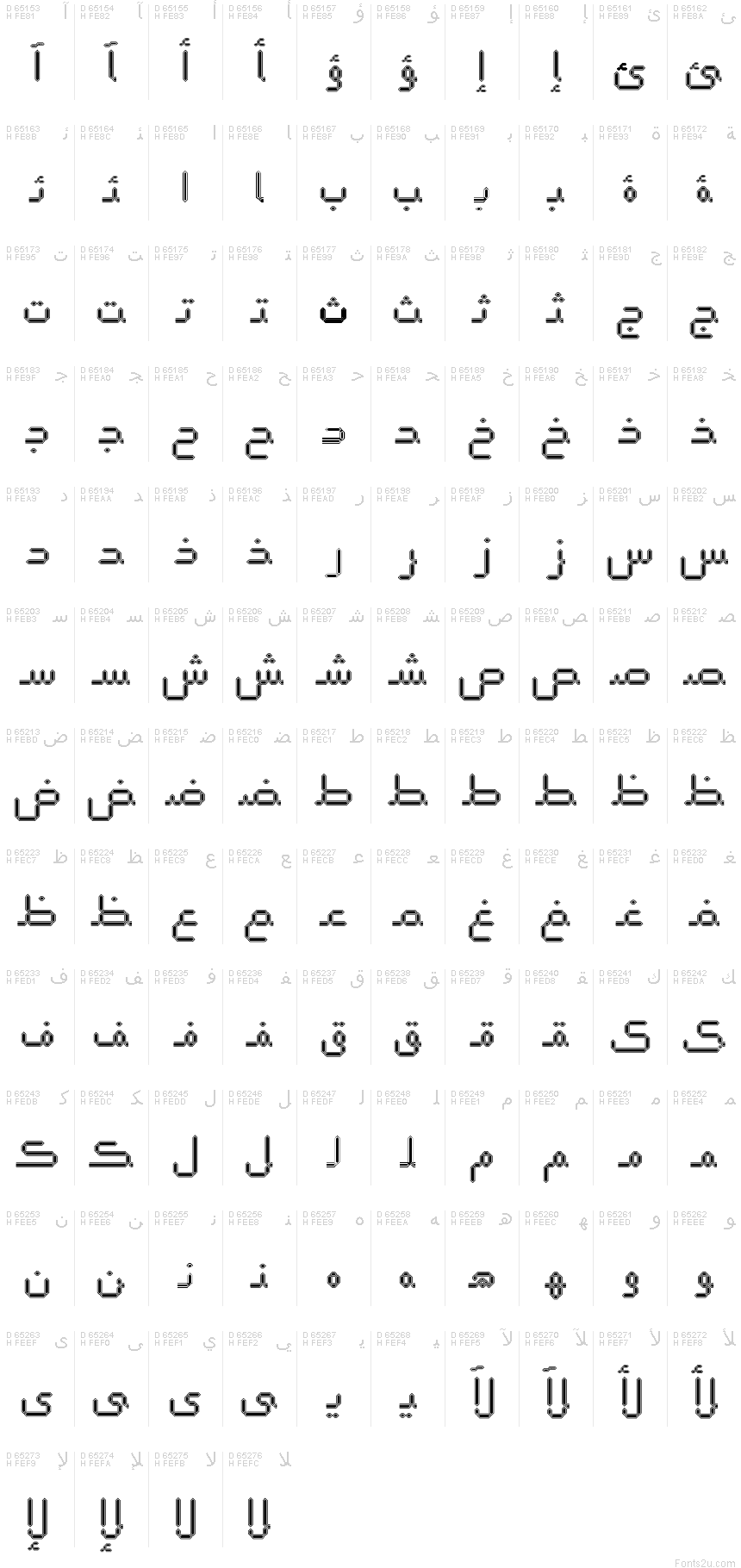
B Elm Border od Borna Rayaneh je bezplatné arabské písmo typu display, ktoré vychádza zo segmentovaného vzhľadu LED a elektronických displejov, pričom túto logiku prispôsobuje arabským písmenám. Obrysová konštrukcia a rovnomerné rozostupy vytvárajú ostrý technický rytmus, vďaka čomu pôsobia písmená skôr ako digitálny displej než ako bežné písmo.
Jeho elektronický charakter z neho robí prirodzenú voľbu pre technologický branding, grafiku rozhraní, herné vizuály, plagáty na podujatia a obaly s digitálnou tematikou, kde sa vyžaduje nezameniteľný štýl inšpirovaný obrazovkami. Písmo tiež spoľahlivo poslúži ako bezplatný font na arabské nadpisy, titulné karty a krátke texty, ktoré ťažia z jeho čistej segmentovanej štruktúry.